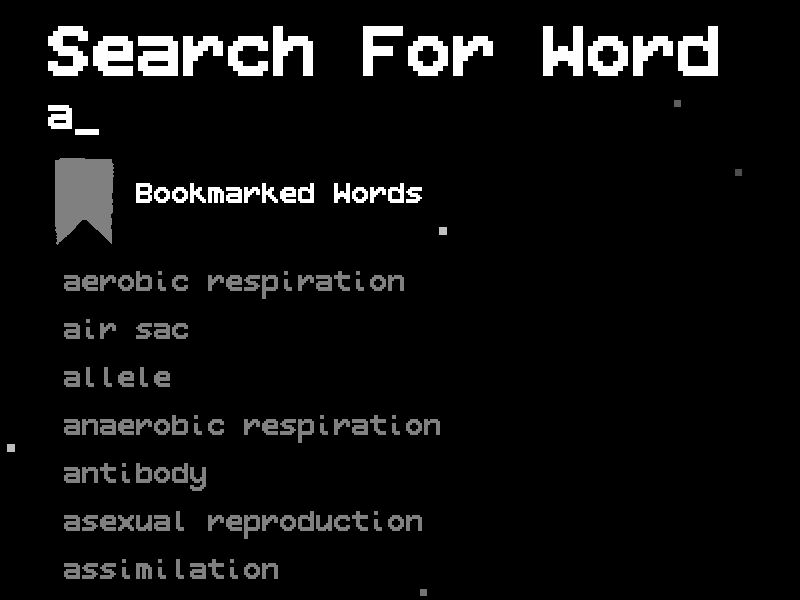
7款专为独立游戏和艺术作品设计的像素Suffirat字体素材,它包含七款字体,每款字体都拥有独特的风格。
- Suffirat
- Suffirat Block
- Suffirat Block Alt
- Suffirat Small
- Suffirat Mini
- Suffirat Straight
- Suffirat Nine
Suffirat、Suffirat Block 及其变体支持 Latin-1 Supplement 和 Latin Extended-A。